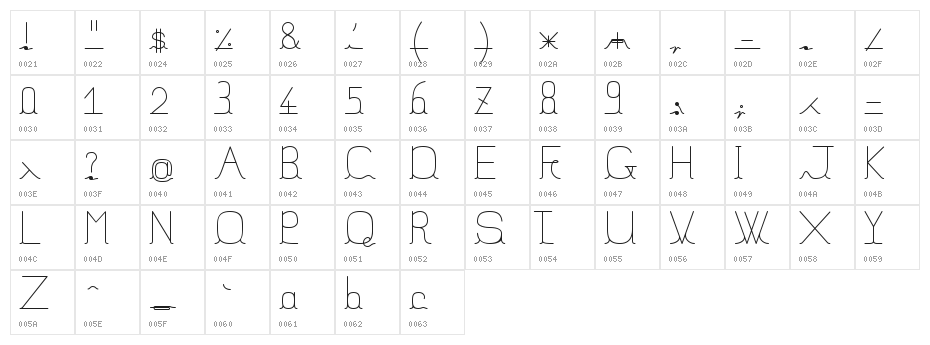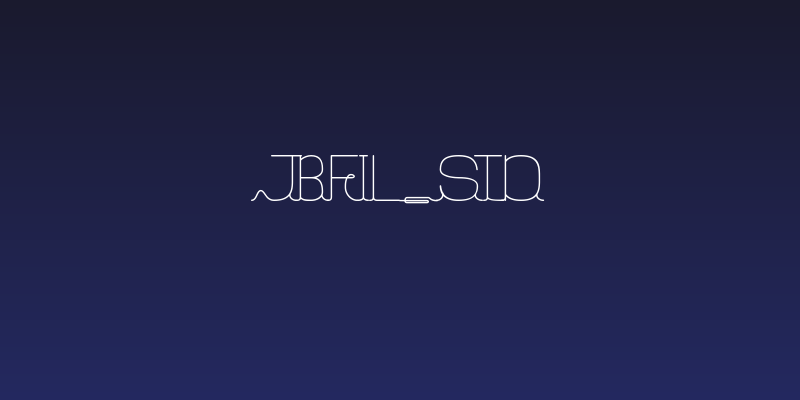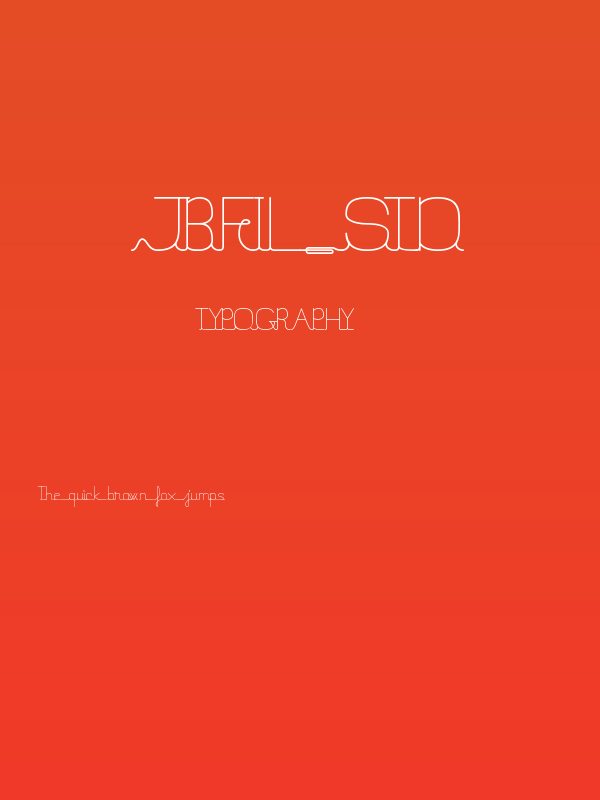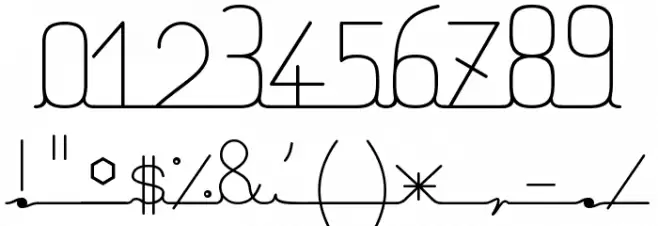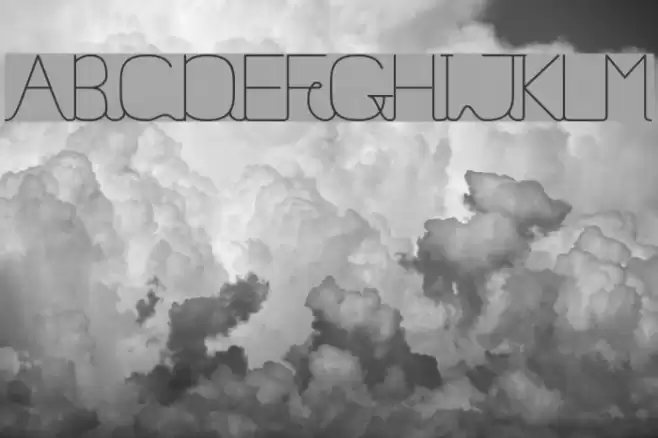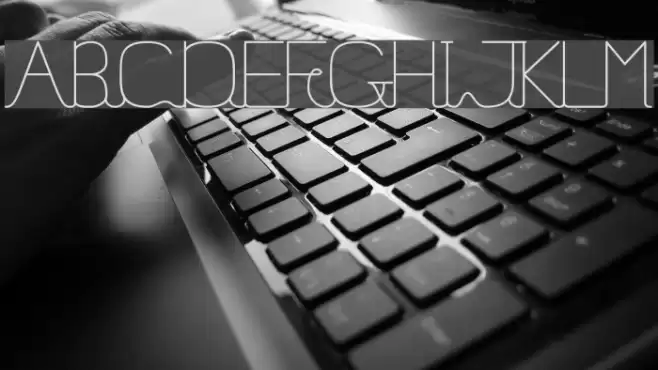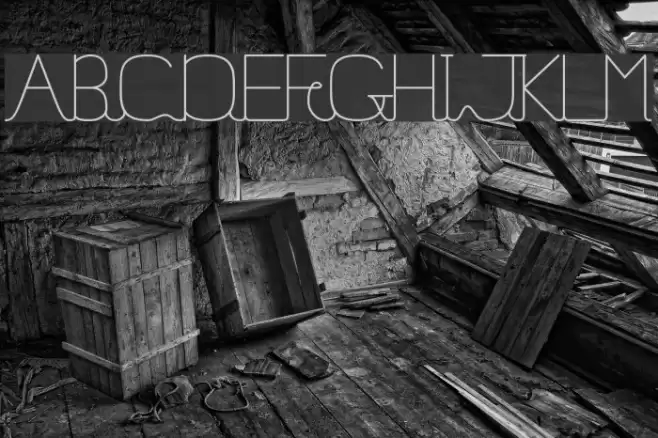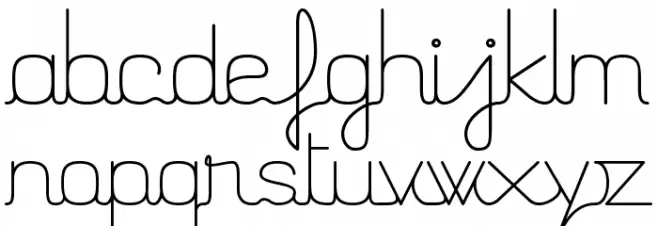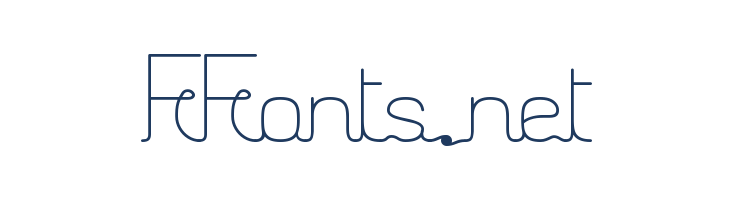
JBFil_std Font
| Caso de uso | Logos, Creative projects, Art installations |
| Proyectos propuestos | Ideal for branding, logos, modern art projects, and creative advertising materials. |